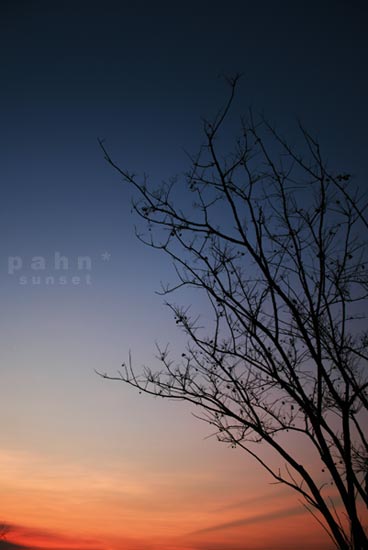
Re: กระจู๋ของคนโชว์รูป
คุ้นๆ ว่าตอบคำถามนี้ด้วยตัวเองไปหลายรอบแล้ว
ทำไปทำมาก็เลยไม่ใส่อะไร ไม่แต่งอะไรลงไปในรูปลยดีกว่า
แอนในยุคแรกจะใส่ตาลงในทุกรูป  เกย์แอบ
อันนั้นเอาไว้กันขโมยย่ะ ชิ
โดยส่วนตัวรู้สึกว่ามันรบกวนรูปยังไงอยู่
กลายเป็นศิลปะการจัดวางตัวหนังสือมากกว่าการถ่ายภาพ
คือจะให้ดูกราฟิกปกหนังสือ หรือจะให้ดูรูปถ่ายกันแน่
บางท่านใส่แล้วก็โอเคนะครับ แต่ส่วนใหญ่คิดว่ามันเด่นกว่ารูป
และถึงจะจัดดี ในแง่องค์ประกอบแล้ว ตัวหนังสือบนรูปถ่ายเหล่านี้มาแย่ง
องค์ประกอบในภาพไปไม่มากก็น้อย
ยกเว้นจะตั้งใจอยู่แล้วว่าจะใช้ทั้งภาพและตัวหนังสือ
สื่อความหมายพร้อมๆกันนะ
อันนั้นเอาไว้กันขโมยย่ะ ชิ
บางคนก็เพื่อการนี้น่ะเก้อ ไหว้
หลังๆมานี่มันเอาไปอ้างกันง่ายดาย
ดูงานของลุงโก้สิ
ใส่ตัวอักษรแล้วช่วยให้ภาพสวยขึ้นมากจ้ะ
แม้จะเป็นภาษาอังกฤษก็เหอะ เจ๋ง
ตูชอบอันนี้ เป็นภาษาไทยด้วย
โอ้ว แค่ User Name ก็เท่มากๆ แล้ว เจ๋ง
ส่วนเรื่องภาษาเห็นว่ามันสวยเลยใส่ลงไปครับ ไอ้มืดหมี
คือจะให้ดูกราฟิกปกหนังสือ หรือจะให้ดูรูปถ่ายกันแน่
บางท่านใส่แล้วก็โอเคนะครับ แต่ส่วนใหญ่คิดว่ามันเด่นกว่ารูป
และถึงจะจัดดี ในแง่องค์ประกอบแล้ว ตัวหนังสือบนรูปถ่ายเหล่านี้มาแย่ง
องค์ประกอบในภาพไปไม่มากก็น้อย
อย่างที่เก้อบอกไว้เลยครับ  เจ๋ง
ผมเองยังทำให้ตัวอักษรที่วางบนภาพ สวยไม่ได้เลย